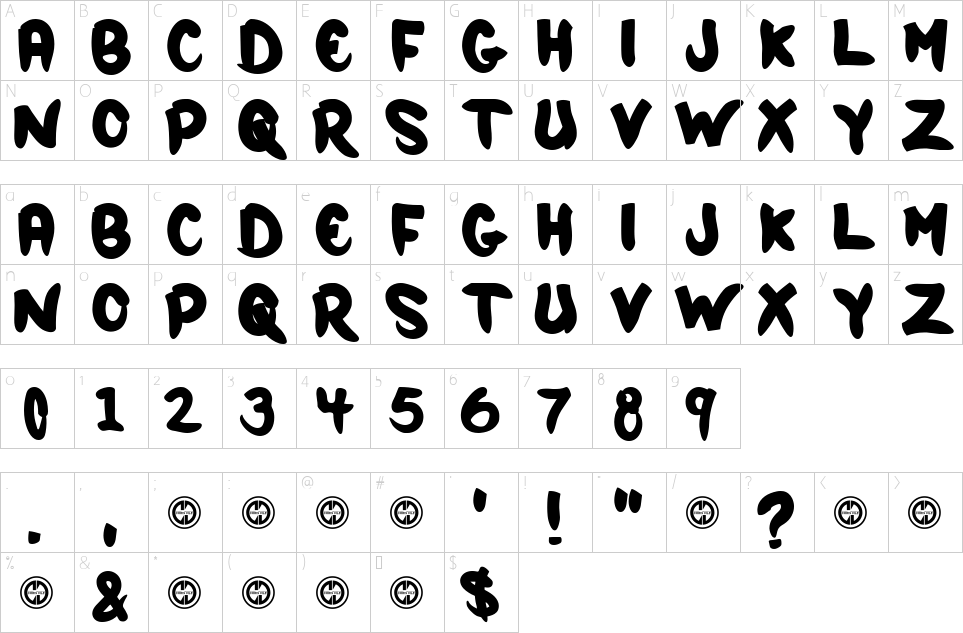
A fonte Sad Szn é um design emotivo e versátil, perfeitamente adaptada para textos emocionais e expressões de humor. Desenvolvida por Font Monger, ela oferece um toque de tristeza e humor que pode agregar valor a um design, seja em cartazes de propaganda, banners de redes sociais ou até mesmo em designs de jogos. Com uma popularidade de 13.494 downloads, Sad Szn está disponível para usuários de Windows e Mac, permitindo que você personalize a aparência de seus projetos com uma fonte que transmite sentimentos de maneira única e impactante. Seja você designer de arte digital, desenvolvedor de jogos ou mesmo criador de conteúdo de redes sociais, Sad Szn é uma excelente adição a seu arsenal de ferramentas de design.